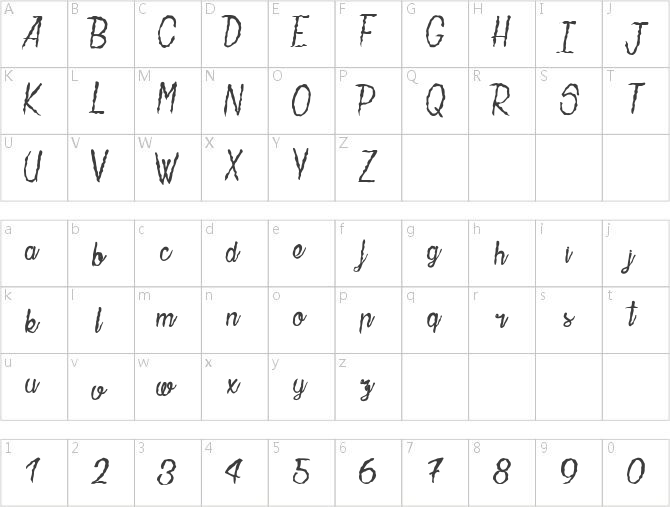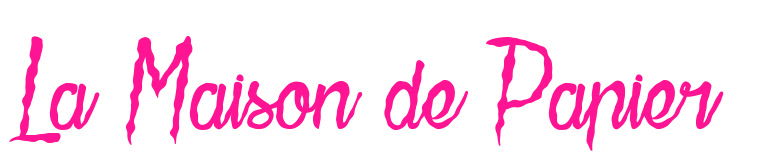
La Maison de Papier
La Maison de Papier字體字庫(kù)是一款讓人賞心悅目、百看不厭的英文字體,適合各類廣告和產(chǎn)品包裝設(shè)計(jì)應(yīng)用,字體大小0.08MB,格式為ttf字體,上傳用戶是迷路的豬,作者/版權(quán)方為未知